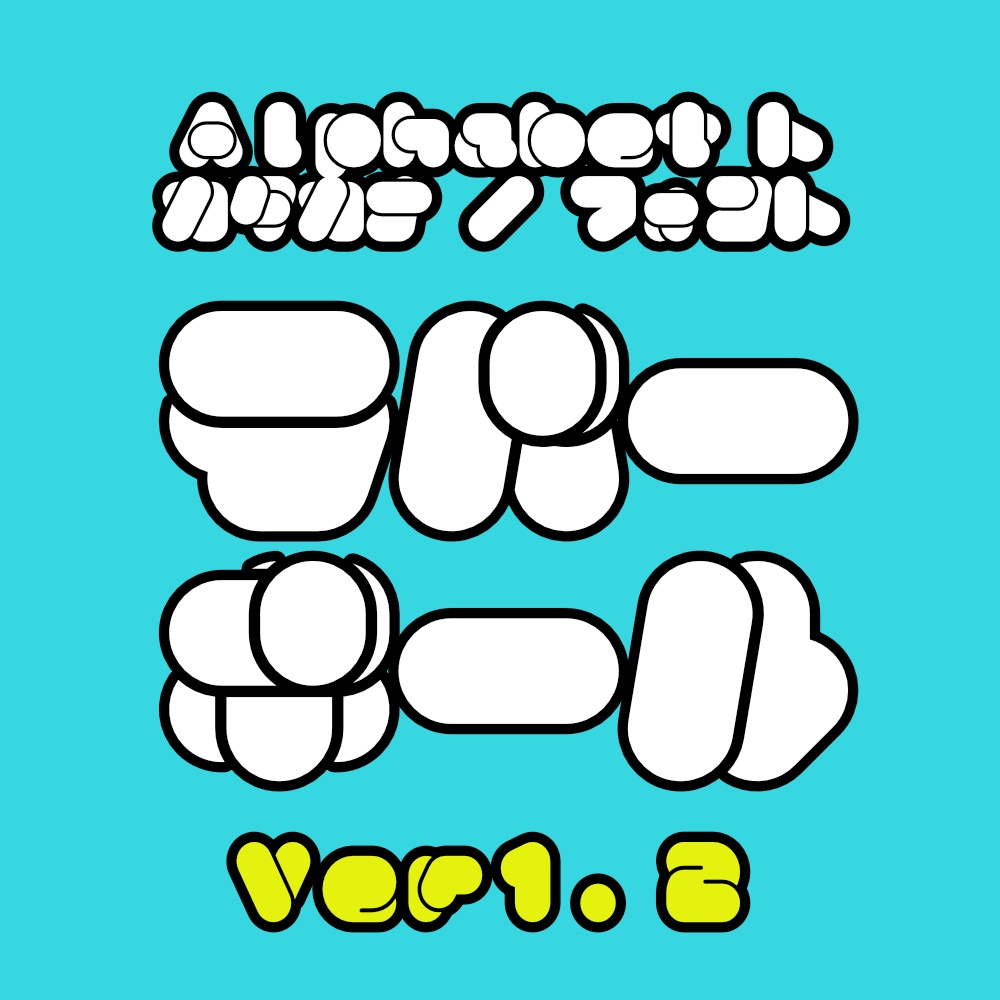
torisippoフォント ラバーボールダウンロード商品¥ 0無料ダウンロードrubberball_1.2d.zip (44.5 KB)rubberball_1.2d.zip「ギフトとして贈る」とはカタカナを極端に太く丸くしました。 フォントデータ形式TrueType(.ttf) OpenType(.otf) 更新履歴2026/02/04 v1.2c グリフの位置修正[l] 2026/01/31 v1.2b グリフのイメージ変更[a:] 2026/01/30 v1.2a グリフのイメージ変更[fmnotuvIOV0[](){}%&+] 2026/01/20 v1.2 アルファベット・数字の追加、oftファイルの追加 2025/03/19 v1.1 "モ"のはみ出しを修正 2024/09/09 v1.0 初版 torisippoFANBOX開設中フォント・書体フォント five keys ファイブキーtorisippo¥ 0フォント・書体フォント Auxiliary line オーグジュアリラインtorisippo¥ 0フォント・書体フォント でんでんえん/でんえんえんtorisippo¥ 1,200フォント・書体フォント DOThoundstooth ドットハウンドトゥース(ドット千鳥格子)torisippo¥ 0フォント・書体フォント ひらすわぷろtorisippo¥ 800フォント・書体フォント PCB10 プリント基板配線パターンフォントtorisippo¥ 0フォント・書体フォント MahjongMPSZColortorisippo¥ 0フォント・書体フォント DOTjigsaw (fontforge用フォント生成スプリクト付き)torisippo¥ 0ソフトウェアFormat Renamer ~キーボードを極力使わないリネームソフト~torisippo¥ 1,000フォント・書体フォント マステ丸 ラウンド25torisippo¥ 0フォント・書体フォント ひらすわtorisippo¥ 0フォント・書体フォント メニーワンtorisippo¥ 0フォント・書体フォント MahjongZSPMtorisippo¥ 0フォント・書体フォント MahjongMPSZtorisippo¥ 0フォント・書体フォント ブルーテイルtorisippo¥ 0フォント・書体フォント デンエンtorisippo¥ 0フォント・書体フォント カールtorisippo¥ 0フォント・書体フォント ウォータービーズtorisippo¥ 0フォント・書体フォント ウーファーtorisippo¥ 0フォント・書体フォント フォースフルドットtorisippo¥ 0もっと見る